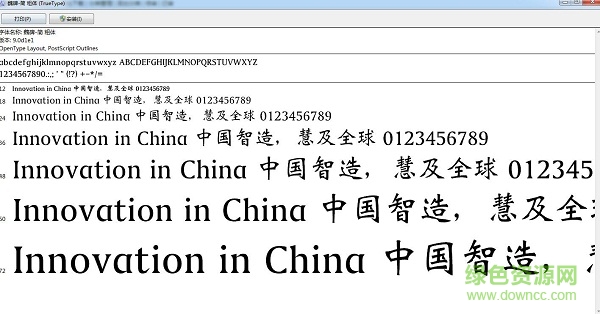
魏碑-簡 bold
魏碑-簡 粗體是一款堅實挺拔的粗體魏碑字體,筆劃嚴(yán)謹,線條舒暢,筆意樸拙,可以用在產(chǎn)品包裝設(shè)計或是們門店招牌設(shè)計,氣質(zhì)極佳,視覺體驗良好,歡迎需要的朋友免費下載!
魏碑簡粗體
魏碑書法字體特征
魏碑書法樸厚靈動,豐腴不失于板刻,上承漢隸,下開唐楷,兼有隸楷兩體之神韻。它的書法藝術(shù)是在漢隸和晉楷的基礎(chǔ)上發(fā)展演化而來的,堪稱漢碑中的上品。古今書家對此碑都給予最高評價,可謂漢碑集成之碑。